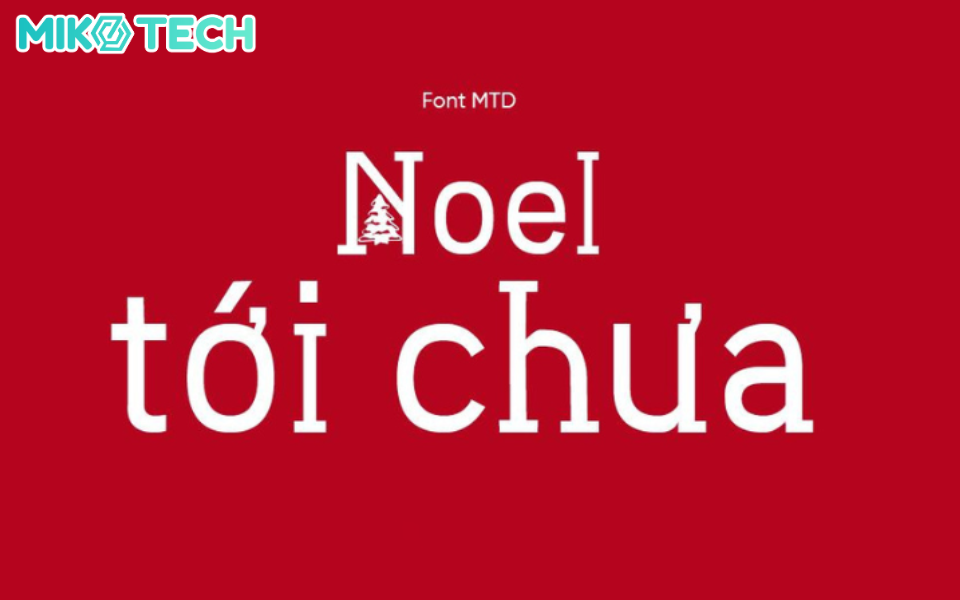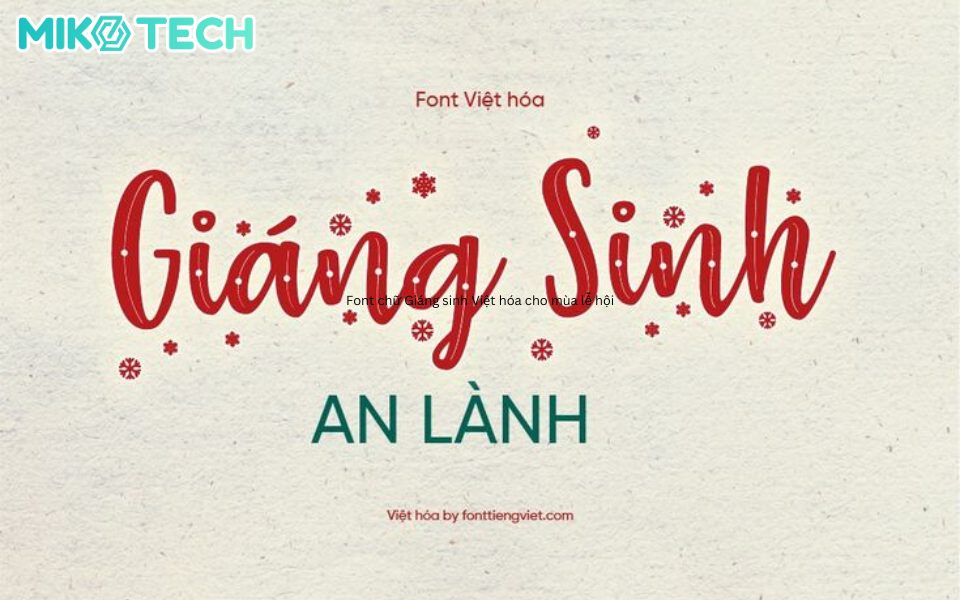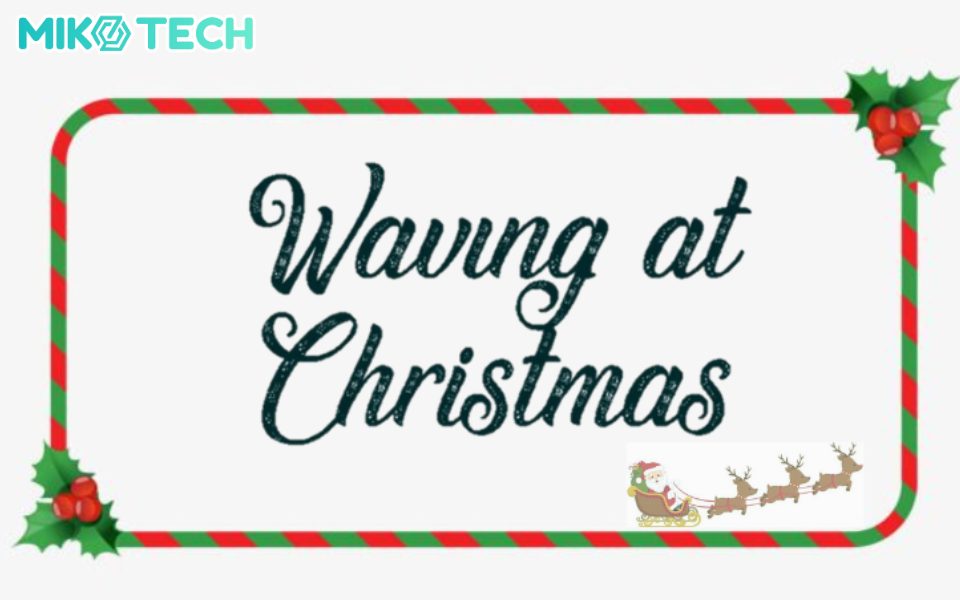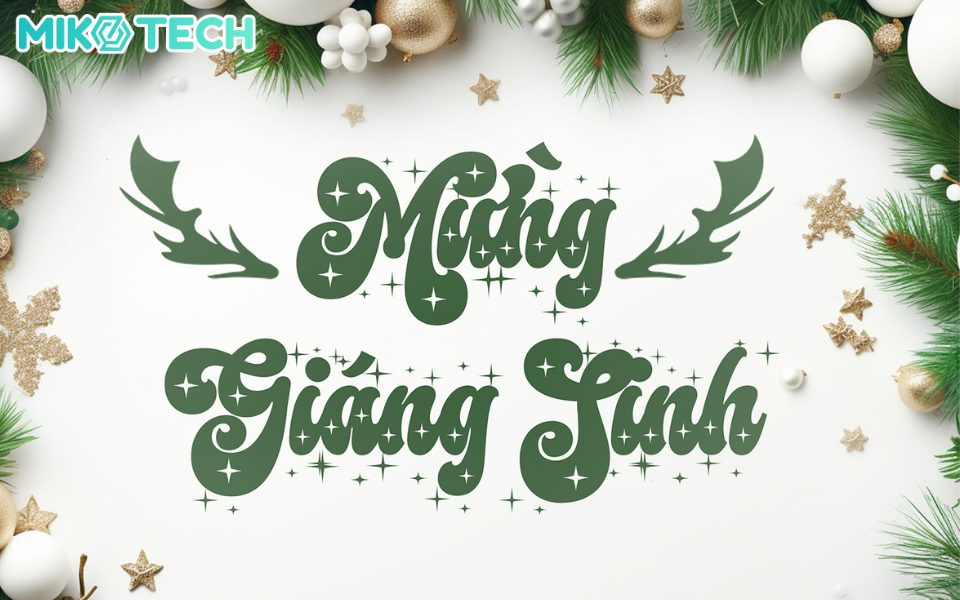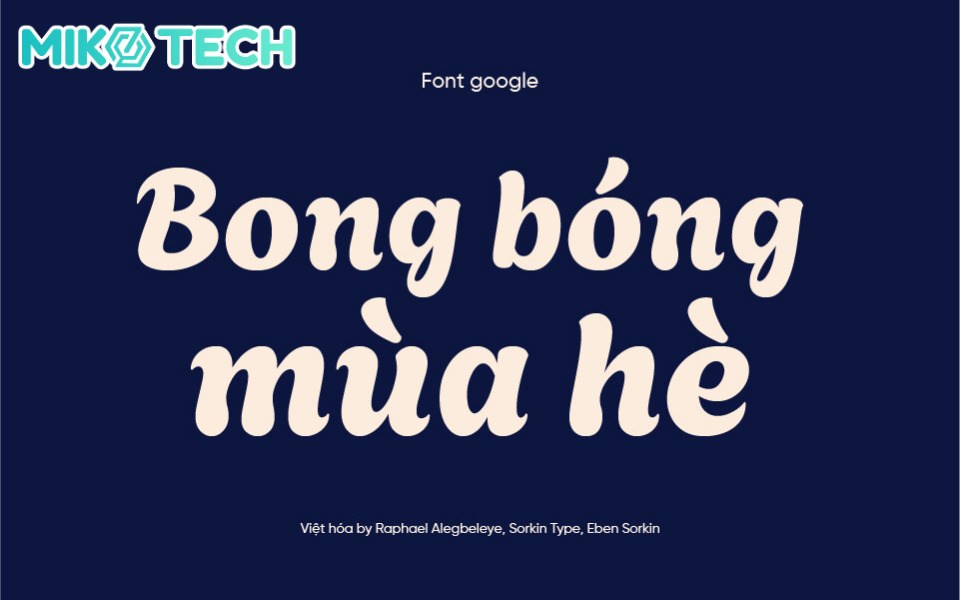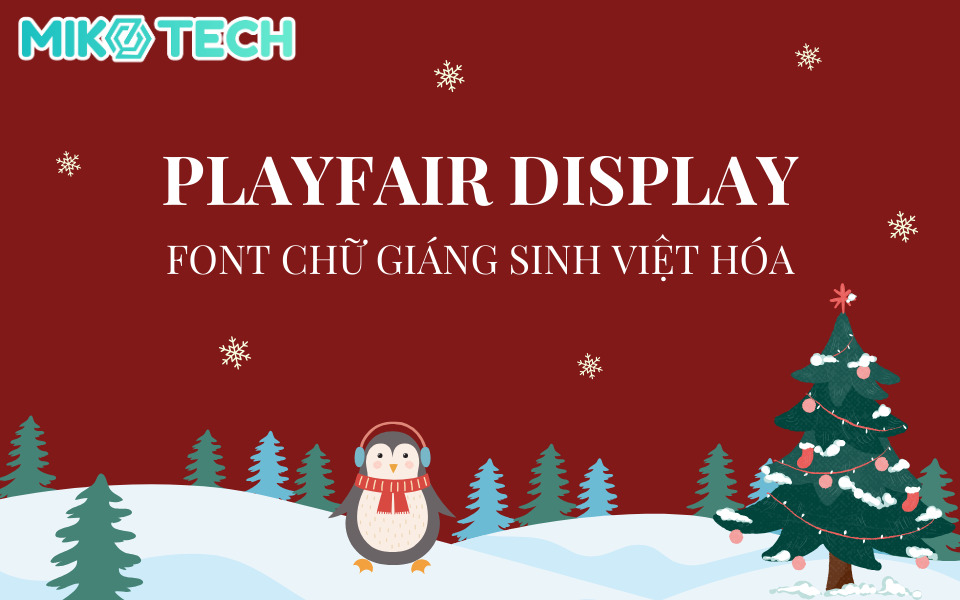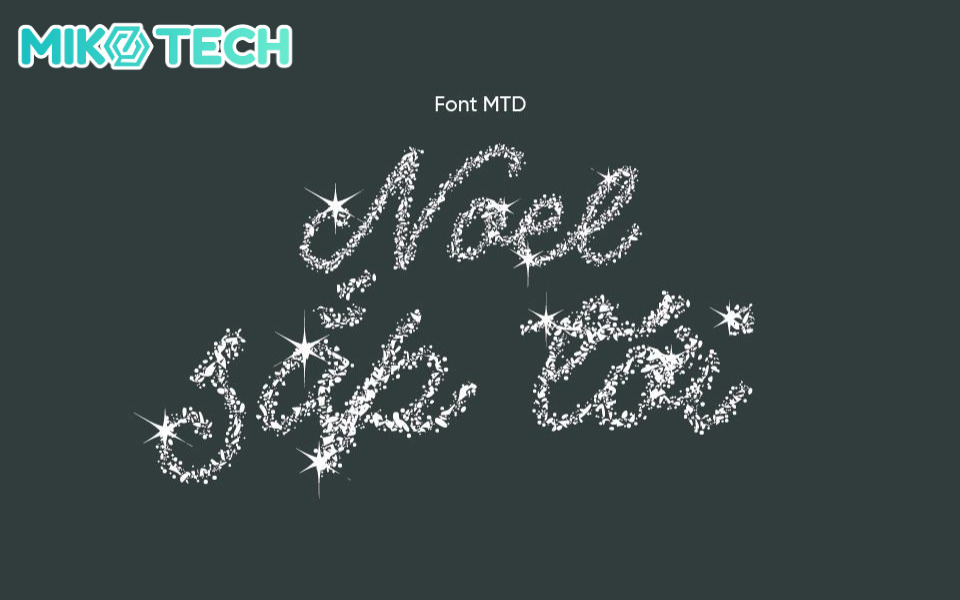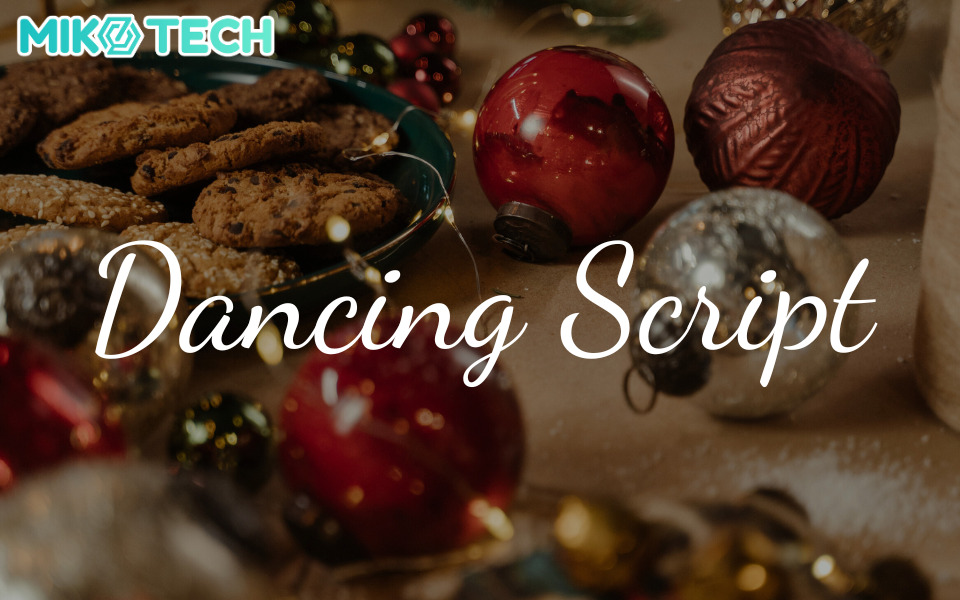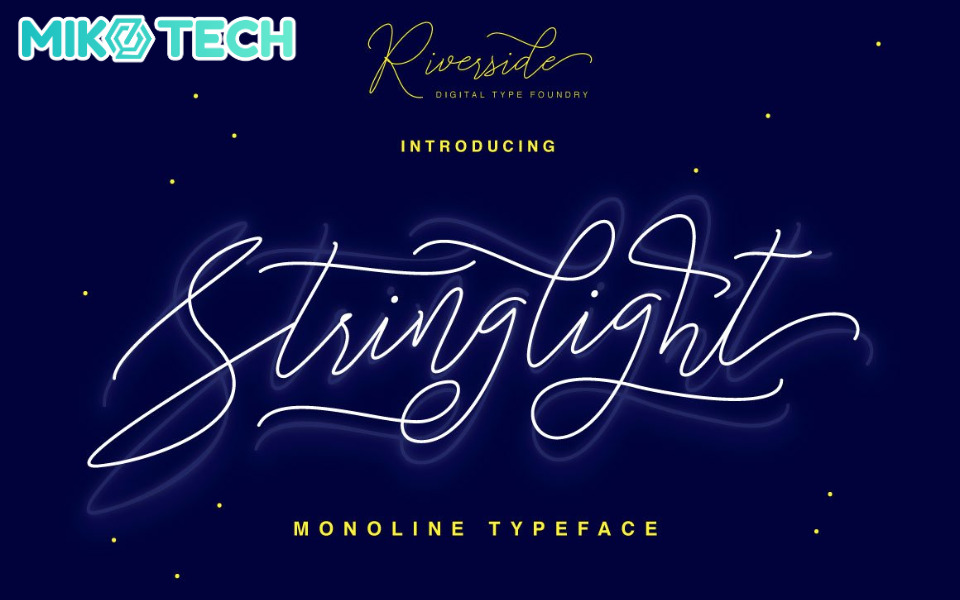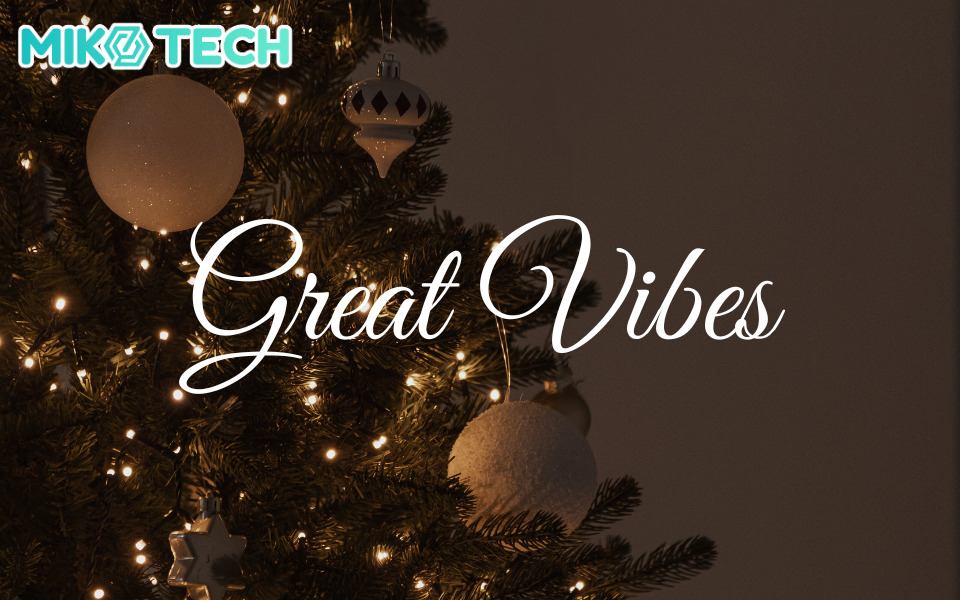
Mùa Giáng Sinh đang đến gần và không khí lễ hội cũng đang tràn ngập khắp mọi nơi! Nếu bạn đang tìm kiếm những font chữ Giáng sinh Việt hóa độc đáo tạo dấu ấn riêng cho các thiết kế của mình, thì bài viết này chính là dành cho bạn. Hãy cùng Miko Tech khám phá cùng bạn bộ sưu tập các font chữ giáng sinh đẹp trong mùa lễ hội này nhé!
Font chữ Giáng sinh Việt Hóa là gì?
Font chữ Giáng sinh Việt hóa là các phông chữ mang phong cách lễ hội Giáng sinh, đã được chỉnh sửa hoặc thiết kế lại để hỗ trợ đầy đủ các ký tự tiếng Việt, bao gồm dấu và các chữ cái mở rộng.
Những font chữ giáng sinh thường mang lại không khí vui tươi, ấm áp hoặc trang trọng, gắn liền với tinh thần của mùa lễ hội. Font chữ viết tay (script) hoặc chữ serif cổ điển là những kiểu thường được sử dụng. Font chữ Giáng sinh Việt hóa được thiết kế đặc biệt với các font chữ mới lạ và thường dùng để thiết kế thiệp chúc mừng, trang trí website, poster quảng cáo, banner…
Top 15+ font chữ Giáng sinh Việt hóa đẹp mắt
Những font chữ mang phong cách mùa đông không chỉ giúp thiết kế trở nên đẹp mắt mà còn truyền tải thông điệp đầy nghệ thuật. Sau đây, Miko Tech sẽ giới thiệu đến bạn những font giáng sinh Việt hóa phổ biến và được sử dụng nhiều nhất hiện nay.
1. Font Arima Madurai
Arima Madurai là một font chữ thích hợp để làm font chữ giáng sinh với thiết kế đặc sắc. Đây là một font chữ hiện đại, với các đường nét mềm mại, dễ đọc và tạo cảm giác tươi mới. Bạn có thể kết hợp thêm các yếu tố trang trí Giáng Sinh như tuyết, cây thông, hay các chi tiết liên quan đến mùa lễ hội để tăng thêm sức hút cho thiết kế.
2. Font Playfair Display
Playfair Display là một font chữ serif mang vẻ đẹp cổ điển, sang trọng. Font chữ này thường được sử dụng trong các thiết kế cao cấp, đòi hỏi sự tinh tế như tiêu đề sách, logo, poster quảng cáo… Playfair Display mang nét đẹp cổ điển, do đó có thể được sử dụng cho các thiết kế giáng sinh cần sự trang trọng.
3. Font Agbalumo
Font chữ giáng sinh Agbalumo là một font chữ độc đáo với những nét cong mềm mại, đậm nét và có phần hơi tròn trịa. Các đường nét mềm mại của Agbalumo rất phù hợp để truyền tải không khí ấm cúng của mùa Giáng sinh. Bạn có thể sử dụng font Agbalumo cho tiêu đề hoặc slogan và kết hợp thêm với các yếu tố trang trí có màu sắc tươi sáng để tạo ra những ấn phẩm giáng sinh ấn tượng.
4. Font DVN Christmas
Font giáng sinh DVN Christmas là một sự lựa chọn tuyệt vời để thiết kế các ấn phẩm cho dịp lễ này. Các ký tự có kiểu dáng cong tròn, mềm mại, được trang trí thêm những họa tiết ngôi sao lấp lánh và thể hiện rõ không khí vui tươi của lễ giáng sinh. Font chữ này không chỉ phù hợp với các thiết kế thiệp chúc mừng, banner hay poster mà còn có thể được dùng cho bao bì sản phẩm phiên bản Giáng sinh.
5. Font The Perfect Christmas
The Perfect Christmas là một font chữ cực kỳ phù hợp với không khí giáng sinh nhờ vẻ đẹp mềm mại, tinh tế và được trang trí thêm bằng những bông tuyết quanh ký tự. Bạn có thể sử dụng font chữ The Perfect Christmas để thiết kế thiệp giáng sinh, các ấn phẩm đặc biệt như poster quảng cáo hoặc thông báo sự kiện mùa giáng sinh.
6. Font For Christmas
For Christmas được sáng tạo bởi Jada Akbal là một font chữ noel với nét chữ uốn lượn mềm mại, đẹp mắt. Đây là một font chữ serif được trang trí thêm bằng những nét đứt và các ngôi sao nhỏ lung linh, rất phù hợp để thiết kế các ấn phẩm theo concept kỳ ảo, ma thuật và cần có sự lung linh ấn tượng.
7. Font Stringlight
Stringlight là một font chữ mang đậm không khí Giáng sinh với thiết kế mềm mại, lãng mạn được lấy cảm hứng từ những dây đèn trang trí lung linh. Các nét chữ uyển chuyển của Stringlight tạo ra cảm giác ấm áp, dễ chịu, hoàn hảo để truyền tải tinh thần lễ hội. Font chữ Stringlight sẽ phù hợp nhất để thiết kế logo, thẻ quà tặng hoặc lời chúc giáng sinh cho khách hàng.
8. Font Pinyon Script
Pinyon Script là một font chữ giáng sinh Việt hóa viết tay đầy quyến rũ, trang nhã và tinh tế. Mặc dù không phải font chữ được thiết kế riêng cho mùa giáng sinh nhưng Pinyon Script có thể mang lại một nét độc đáo cho các thiết kế mùa lễ hội. Font chữ Pinyon Script đặc biệt lý tưởng để thiết kế thiệp chúc mừng, thư mời, hay bất kỳ thiết kế nào cần sự trang trọng và lãng mạn.
9. Font Great Vibes
Great Vibes là một font chữ giáng sinh đẹp với phong cách thanh lịch, uyển chuyển. Điểm đặc trưng của nó là các ký tự liên kết liền mạch, chữ in hoa phong cách và các nét lên xuống mềm mại, mượt mà. Great Vibes có thể được dùng để thêm nét sang trọng cho các thiết kế giáng sinh, đặc biệt là thiệp giáng sinh, thiệp mời dự tiệc giáng sinh hoặc bao bì quà tặng.
10. Font MTD Christmas Miracle
Font chữ noel MTD Christmas Miracle mang đến không khí lễ hội ấm áp và huyền diệu của mùa Giáng Sinh. Với thiết kế lấp lánh như những ánh sao giữa trời đông kỳ ảo, font chữ này có thể được dùng để thiết kế các thông báo đặc biệt, poster hoặc teaser cho event trong mùa giáng sinh.